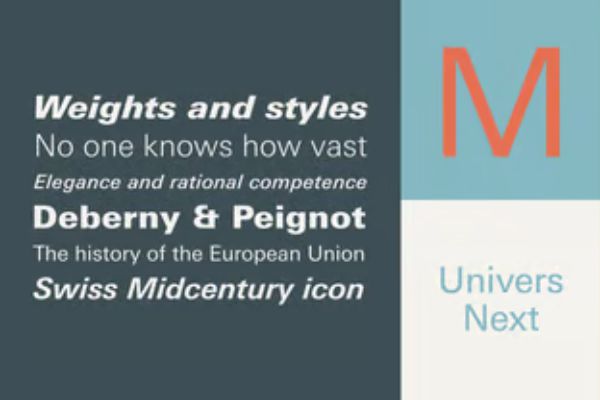
Univers® Next Pro 241 Extended Thin Italic
Univers Next 是原始 Univers 字体的完全重制版本,使比例更加一致并改进细节,以提高易读性和屏幕应用。由于其易读性,Univers Next 应用于索尼一款电子书阅读器,也会在许多 POP摊位和其他零售相关标牌上找到该字体。